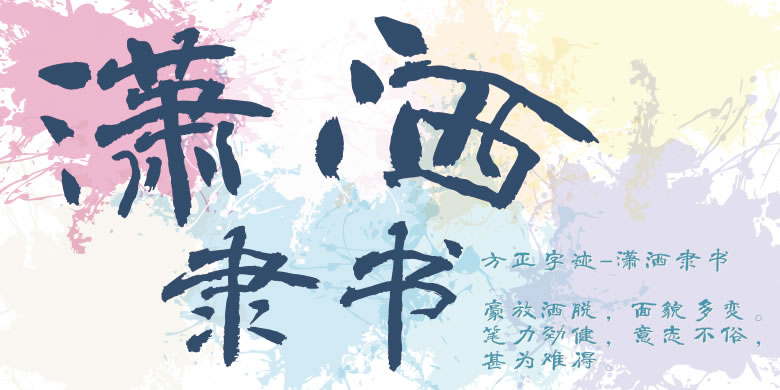
方正字迹-潇洒隶书繁体
品牌:方正字迹设计师:顾建平发行时间:2011字库编码:大陆简体(GB2312-80)、大陆繁体(GB12345-90)分类:常规书写·毛笔
由新加坡著名书法家顾建平创作。顾建平刻苦钻研书法四十年,融会篆隶楷行草,兼修书法内外功,在创作、研究、教学、著述各方面均有建树。书法作品,各体兼善、豪放洒脱、面貌多变,原中国书法家协会主席赵朴初赞其:“笔力劲健,意态不俗,甚为难得”。曾在中国、新加坡3次举办个人大型书法展,书法作品在11个国家展出,受邀入总统府挥毫表演与总统合影,书法作品为女王、皇太子、总统、总理、副总理、部长收藏。方正字迹-潇洒隶书体秀逸似《司晨》,古拙近《张骞》,奔放若《石门》,兼融篆行草,意趣古穆,体态恣肆,呈多元复合之美,赋予隶书新的艺术生命。